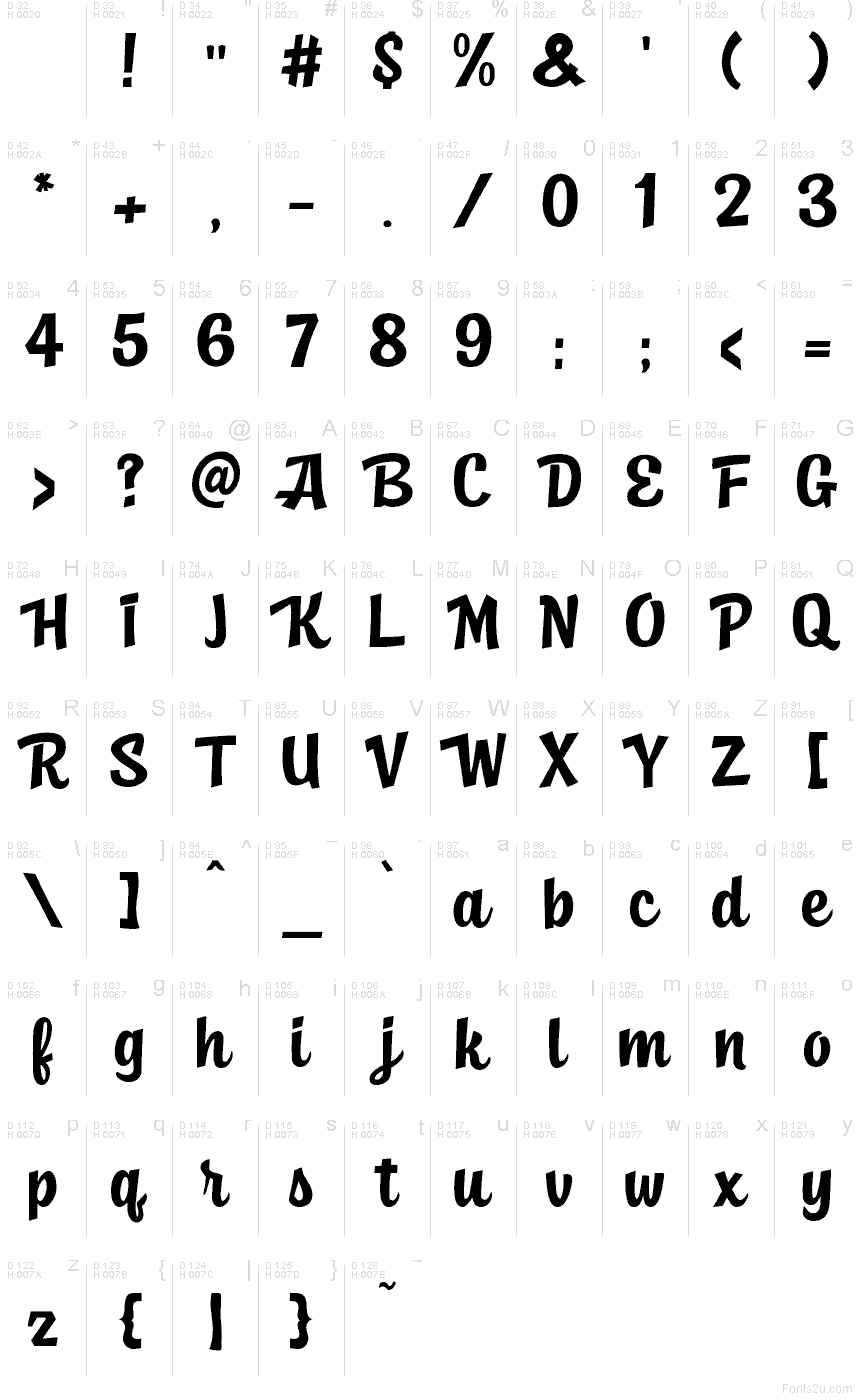
Wakeboard Studio от BlackFridayFont — это бесплатный шрифт с эффектом кисти, быстрым «рукописным» штрихом и легким налетом ретро-эстетики серфинг-шопов. Буквы выглядят широкими и живыми, с толстыми мазками, плотными соединениями и закругленными линиями, что сохраняет непринужденный вид надписей, не переходя в небрежный почерк.
Он отлично подойдет для принтов на одежде, брендинга пляжной тематики или серфинг-брендов, вывесок кафе, заголовков на плакатах и упаковке, где важнее движение, чем идеальная выверенность. Используйте его для коротких заголовков, обложек или логотипов, когда хотите, чтобы шрифт выглядел нарисованным одним движением, с достаточным весом и энергией, чтобы передать расслабленное настроение, выгоревшее на солнце.